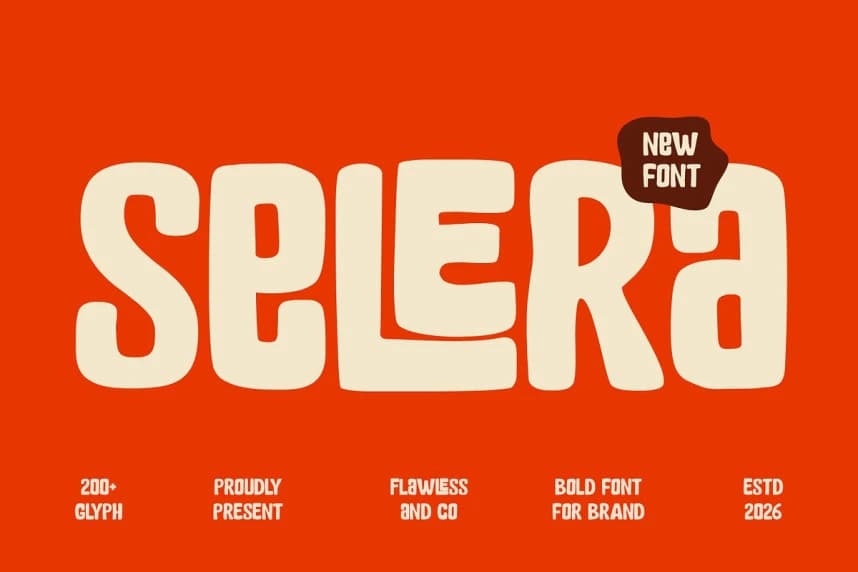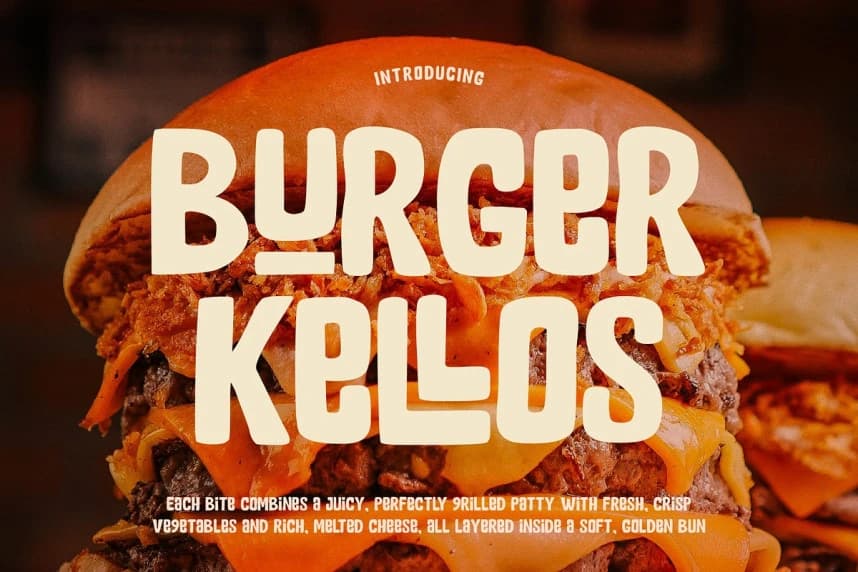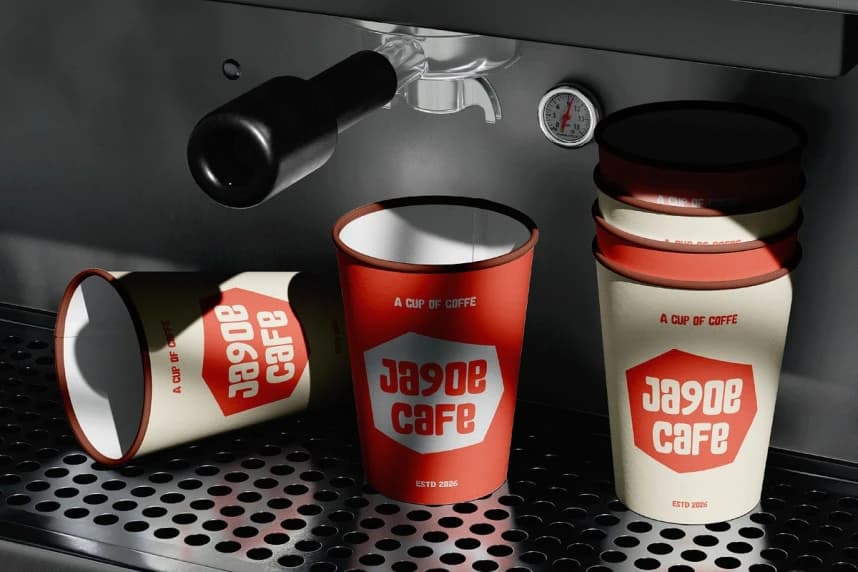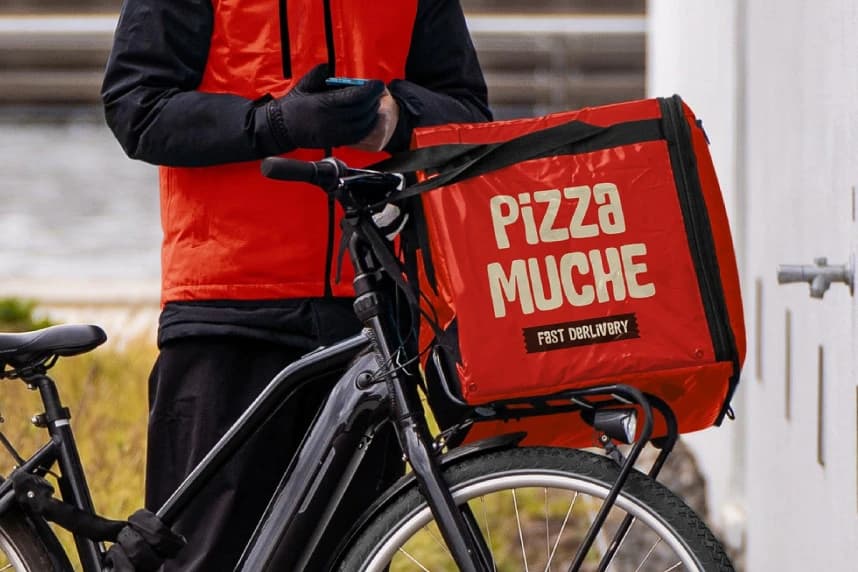
Selera Font
Selera Font, eğlenceli, lezzetli ve dikkat çekici bir görsel deneyim yaratmak için tasarlanmış modern, kalın bir gösteri tipografisidir. Enerjik marka stillerinden ilham alan Selera, kalın blok harf formlarına ve yumuşak kenarlara sahiptir.